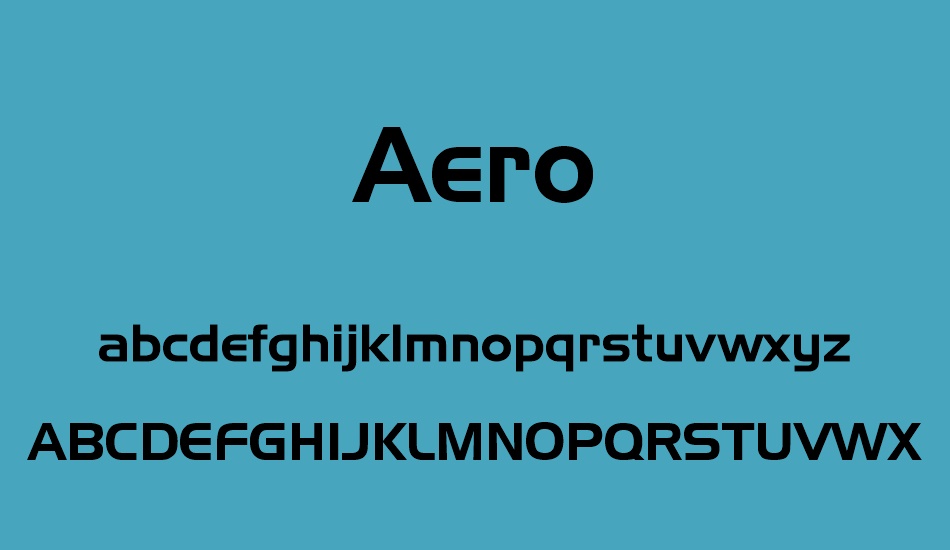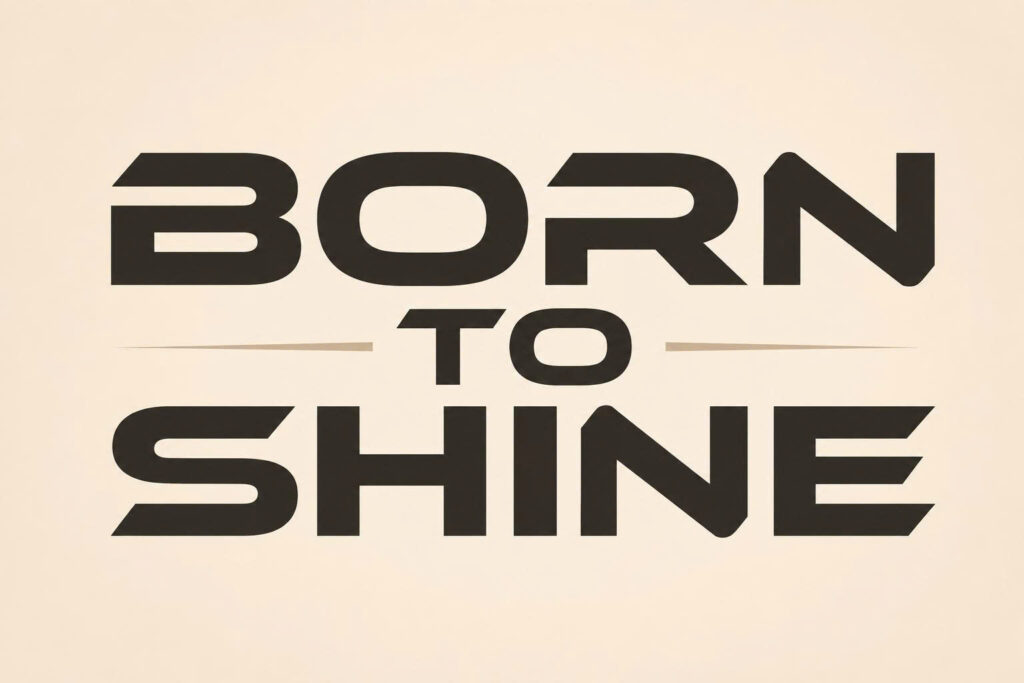
Font Aero Việt hóa là bộ phông chữ thuộc dòng Futuristic Display mang đậm cảm hứng từ ngành kỹ thuật hàng không vũ trụ và các đường cong khí động học (Aerodynamic) với các góc lượn đón gió, độ nghiêng tốc độ và cấu trúc hình học tinh giản. Với diện mạo thanh thoát, giàu tính công nghệ và tràn đầy tinh thần bứt phá, tải font Aero Việt hóa là chất liệu trực quan tuyệt vời để các kiến trúc sư, nhà thiết kế mang lại sự tươi mới cho các bản vẽ phối cảnh trạm sạc thông minh container, văn phòng nghiên cứu công nghệ cao hay hệ thống biển chỉ dẫn nhà ga hiện đại.
Đường nét khí động học và tinh thần hàng không của font Aero Việt hóa
Điểm cuốn hút của font Aero Việt hóa nằm ở sự kết hợp tài tình giữa các đường bo tròn mềm mại ở góc đón gió và các đường cắt vát sắc nhọn dứt khoát ở phần đuôi chữ, mô phỏng sinh động chuyển động xé gió của cánh máy bay phản lực. Cấu trúc ký tự sở hữu độ mở thông thoáng, chiều ngang chữ nở rộng hào phóng mang lại nhịp điệu thị giác nhanh nhẹn, loại bỏ hoàn toàn sự ỳ ạch của các kiểu chữ đồ họa truyền thống.
Sự ổn định về mặt cảm xúc của dòng font này tạo nên cảm giác tân tiến, tự do và hướng đến tương lai rộng mở. Khi kết hợp cùng các vật liệu kiến trúc hiện đại như tấm nhôm uốn cong alu, kính phản quang ánh bạc, khung thép siêu nhẹ hay dải đèn LED âm trần trong các căn nhà lắp ghép module, Aero tạo nên sự hòa quyện thẩm mỹ tương lai vô cùng bắt mắt.
| Phân loại phong cách | Aerospace Display / Futuristic / Streamlined Sans |
| Mục đích phù hợp | Biển tên trung tâm công nghệ, logo khí động học, poster |
Tư vấn từ chuyên viên: Aero sở hữu các góc vát nghiêng giàu năng lượng chuyển động. Để bản thiết kế đạt hiệu quả thẩm mỹ tốt, bạn nên sử dụng phông chữ này cho các tiêu đề chính, tên dự án hoặc con số kỹ thuật ở kích thước lớn.
Nhờ vẻ ngoài thanh thoát và tính gợi hình tốc độ phong phú, bộ phông chữ này mang lại giá trị thực tế lớn trong khâu tạo điểm nhấn cho các công trình hiện đại:
- Biển hiệu mặt tiền cho Trạm điều hành và Phòng Lab Container: Những khối chữ lượn sóng khí động học của Aero rất ăn ý khi gia công chữ nổi bằng alu gương bạc hoặc inox xước viền LED xanh dương, mang lại diện mạo không gian vũ trụ thu hút mọi ánh nhìn.
- Hệ thống biển chỉ dẫn phân khu Trạm dịch vụ sạc xe điện: Phông chữ này khi in trên các tấm kim loại sơn tĩnh điện phủ nano sẽ giúp các trạm sạc lắp ghép toát lên phong thái năng lượng sạch, tạo cảm giác thân thiện với môi trường và hướng đến tương lai.
- Bìa hồ sơ ý tưởng kiến trúc công trình siêu nhẹ: Sử dụng font Aero Việt hóa cho tên dự án giúp tập hồ sơ toát lên vẻ ngoài của một công trình ứng dụng vật liệu hàng không tân tiến, tạo niềm tin lớn với các chủ đầu tư yêu chuộng giải pháp đổi mới.
Để khai thác hiệu quả vẻ đẹp của dòng font khí động học này mà không gây cảm giác chông chênh cho bản vẽ, người thiết kế nên lưu tâm một số kinh nghiệm sau:
- Bố trí khoảng trống thoáng đãng: Do các con chữ có xu hướng nghiêng nhẹ và vươn dài về phía trước, bạn nên chừa khoảng thở rộng rãi xung quanh tiêu đề để đường nét khí động học có không gian lan tỏa cảm giác tốc độ, tránh chèn ép bởi các chi tiết đồ họa phụ trợ.
- Tránh sử dụng cho văn bản dài: Cấu trúc vát góc và độ nghiêng đặc thù của Aero không phù hợp cho các đoạn văn bản giải thích chi tiết. Hãy giới hạn sử dụng cho các cụm từ ngắn từ 2 đến 4 từ để tạo điểm nhấn thị giác tập trung.
- Lựa chọn gam màu kim loại và ánh sáng lạnh: Aero phát huy hiệu quả thị giác cao khi phối cùng các tông màu mang sắc thái tương lai như bạc ánh kim, trắng tuyền, xanh da trời điện tử hoặc xám titan trên nền vật liệu phẳng mờ.